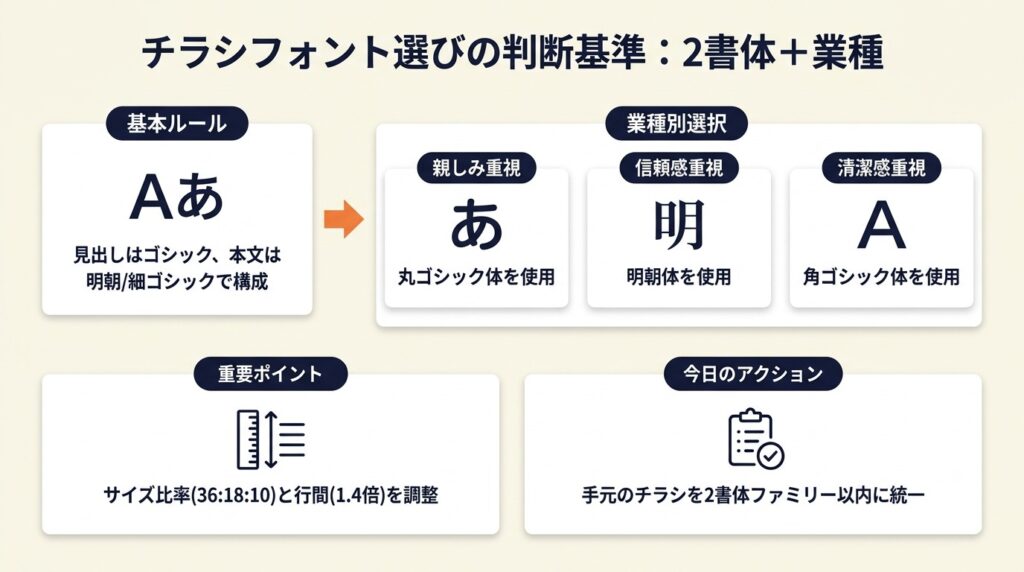
チラシに使うフォントは、ゴシック体・明朝体・丸ゴシックの3系統を業種で使い分けるだけで、読まれるチラシになります。この記事では初心者でも迷わない選び方から業種別おすすめまで7選で解説します。
この記事でわかること
3系統の使い分けルールを知ることで、フォント選びで迷う時間をゼロにできます。業種別5パターンを参照するだけで、読み手の印象と業種がぴったり合うフォントを即座に選べます。商用利用可の無料フォント7選とライセンス確認の2ステップも分かります。
この記事の結論
チラシのフォント選びで最も押さえるべきは「1チラシ2書体ルール」です。ゴシック体を見出しに、細ゴシックまたは明朝体を本文に割り当てるだけで、初心者でも読みやすいチラシが仕上がります。業種別の判断基準は「親しみ重視なら丸ゴシック、信頼感重視なら明朝体、汎用性重視なら角ゴシック」と覚えておけば、フォント選びで迷う場面は大幅に減ります。
今日やるべき1つ
手元のチラシ原稿を開き、見出しと本文のフォントが異なる書体ファミリーになっているか確認してください。同じファミリー内で太さだけ変えるだけで、まとまりが生まれます(5分)。
チラシ フォントは3系統で使い分ける
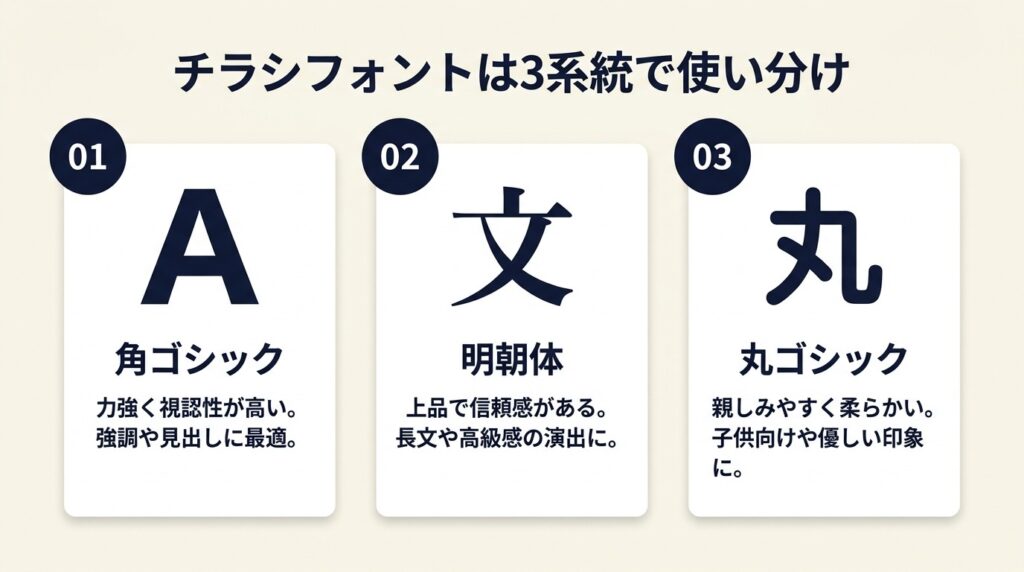
和文フォントだけでも数千種類が存在するため、選択肢の多さに圧倒されるのは自然です。ただし、覚えるべき系統は3つだけです。角ゴシック・明朝体・丸ゴシックの用途と特徴を把握すれば、どんな業種のチラシでも判断に迷わずフォントを選べます。
角ゴシックは見出しに最適なフォント
角ゴシック体は縦横の線幅がほぼ均等で、遠くから見ても文字の輪郭が崩れにくい構造を持っています。メイリオ・游ゴシック・ヒラギノ角ゴシックが代表格で、いずれもOSに標準搭載されているため追加費用なしで使えます。見出しに角ゴシックのBoldウェイトを使うと、A4チラシを腕の長さ分(約60cm)離して見ても文字が判読できる水準の視認性が確保できます。全体をゴシックで統一すると文字の密度感が均一になりすぎて重要箇所が埋もれる点は意識しておいてください。
明朝体は女性向け・高級感チラシで読みやすいフォント
明朝体は横線が細く縦線が太いという線の強弱と、文字末端の「うろこ」と呼ばれる三角形の飾りが特徴です。游明朝・ヒラギノ明朝が代表例で、エステ・ジュエリー・飲食の高単価メニューを訴求するチラシで特に効果を発揮します。本文への使用は12pt以上を確保してからにしてください。小サイズでは横線が潰れて読みにくくなります。
丸ゴシックは子ども向け・親しみやすさを出すフォント
丸ゴシックはゴシック体の線幅均等さを保ちつつ、文字の角を丸く処理したフォントです。Rounded M+ややさしさゴシックが代表格で、幼稚園・保育園の案内、地域イベント、子育て支援サービスのチラシで採用されることが多い書体です。ビジネス向けや高額商品のチラシに使うと「軽い印象」に見える場合があるため、業種との相性を事前に確認してください。
手書き風・筆書体は強調ポイント限定で使うフォント
ふい字・てがき風フォント・毛筆系フォントは、チラシ全体ではなく「本日限り」「数量限定」などの強調コピーに1箇所だけ使うのが基本です。2箇所以上に使うと読み手の視線が散漫になり、どこが最も重要なメッセージかが伝わらなくなります。「1チラシで1カ所限定」と覚えておくだけで、乱雑な印象を防げます。なお、数字フォントのおしゃれな変え方についても参考にすると、価格表記部分の印象が格段に向上します。
▶ 今すぐやること: 手持ちのチラシを開き、使用フォントが「ゴシック系」「明朝系」「その他」の何系統かを数えてください。3系統以上あれば今日中に2系統以内に絞る(10分)
よくある質問
Q: ゴシック体と明朝体はどちらが読みやすいですか?
A: 用途で判断してください。遠くから見るポスター・見出しにはゴシック体、長い本文テキストには明朝体が適しています。初心者はまずゴシック体1系統に絞るのが最もシンプルな出発点です。
Q: チラシに使うフォントは何種類まで使っていいですか?
A: 原則として1チラシあたり2書体ファミリーまでです。同じファミリーの中でRegular・Bold・Lightを使い分けるのは問題ありません。3書体以上になると統一感が崩れる原因になります。
業種別チラシ フォントは5パターンで選ぶ
業種ごとに読み手が無意識に期待している「印象の文法」があります。それに外れたフォントを使うと、内容より先に「なんか違和感がある」と感じさせてしまいます。以下の5パターンを参照して、業種に合ったフォントを即座に選んでください。
飲食店チラシは明朝体か手書き風で食欲を刺激するフォント
飲食店のチラシで最もよく使われる組み合わせは、キャッチコピーに手書き風フォント(ふい字・やさしさゴシック)、店名・メニュー名にヒラギノ明朝、価格や営業時間に游ゴシックという構成です。手書き風は「手作り感・温かみ」を演出し、明朝体は「素材へのこだわり・上品さ」を伝えます。客単価3,000円以上のフレンチやイタリアンでは手書き風を避け、明朝体を中心にすると価格帯に合った品格が出ます。
不動産・建築チラシは明朝体かDINで信頼感を出すフォント
不動産・建築業界のチラシで選ばれることが多いのは、游明朝・ヒラギノ明朝と欧文サンセリフ(DIN・Helvetica)の組み合わせです。明朝体は「誠実さ・長期的な信頼」を想起させる書体で、高額取引を伴う不動産の購買心理に合っています。物件名や価格の数値部分にDINなどの欧文フォントを使うと、和欧混在の文字列がすっきりまとまります。不動産・金融系では丸ゴシックの使用は避けてください。「カジュアルすぎて信用感が下がる」と感じる読み手が一定数います。
子ども・教育向けチラシは丸ゴシックで親しみを出すフォント
幼稚園・学習塾・子育てイベントのチラシでは、Rounded M+・やさしさゴシック・キッズフォントが定番です。丸ゴシックは視覚的なやさしさだけでなく、保護者が「安心・安全な場所」と感じるデザイン上の信号として機能します。本文テキストは最低10pt以上を確保してください。8pt以下になると丸い字形が潰れて逆に読みにくくなります。
医療・健康チラシはゴシック体のみで清潔感を出すフォント
病院・クリニック・薬局・健康食品のチラシでは、手書き風や筆書体の使用を避け、游ゴシック・ヒラギノ角ゴシックのみで統一するのが基本です。医療分野で読み手が求めているのは「正確さ・清潔さ・信頼性」であり、フォントの装飾性は逆効果になります。文字色も黒・紺・グレーに絞り、フォントの種類を増やす代わりにウェイト(太さ)の差で見出しと本文を区別する方法が最もシンプルに機能します。
美容・エステチラシはセリフ系明朝と細ゴシックで女性向け高級感を出すフォント
美容院・エステ・ネイルサロンのチラシでは、ロゴたいぷゴシック・丸明オールド・ヒラギノ明朝といった繊細な線のフォントが好まれます。BoldウェイトよりLightやRegularウェイトを全面に使うことで、余白と細い文字が共鳴して高級感が生まれます。同じデザインレイアウトでもフォントをBoldから明朝Regularに変えるだけで、仕上がりの印象が格段に上がります。チラシのデザイン作成にはCanvaのテンプレートを活用すると、フォントペアリングを効率よく確認できます。
▶ 今すぐやること: 自分の業種を上記5パターンから選び、推奨フォントのうち1つをCanvaまたはWordでテスト入力して印刷プレビューを確認する(10分)
よくある質問
Q: 飲食店のチラシで明朝体と手書き風はどちらが効果的ですか?
A: 業態の価格帯で判断するのが最適です。ランチ1,000円以下のカジュアルな飲食店には手書き風、客単価3,000円以上の和食・フレンチ・イタリアンには明朝体を選ぶと、価格帯と印象が一致します。
Q: 医療チラシで明朝体を使ってはいけないですか?
A: 絶対禁止ではありません。ただし、明朝体の「繊細な横線」が小サイズで潰れやすいため、高齢者向け医療チラシでは読みにくくなるリスクがあります。確実に読んでもらいたい場合はゴシック体を優先してください。
チラシ フォント選びの失敗を3分で診断
「自分のチラシが今どの失敗パターンに当てはまるか」を判定できると、修正ポイントがすぐに特定できます。以下の質問に順番に答えることで、3分以内に対処すべき問題が明確になります。
Q1: チラシに使っているフォントの書体ファミリーは何種類ですか?
3種類以上 → Q2へ。2種類以下 → Q3へ。
Q2: 3種類以上使っているフォントは、それぞれ「見出し用」「本文用」「強調用」と役割が明確に決まっていますか?
役割が決まっていない →Result A(書体の役割が未定義)。役割が決まっている → Q3へ。
Q3: 最も小さい文字サイズは何ptですか?
8pt以下 →Result B(サイズ不足で潰れリスクあり)。9pt以上 → Q4へ。
Q4: 業種と使用フォントの印象は一致していますか?(例:医療×手書き風、不動産×丸ゴシック)
一致していない →Result C(業種ミスマッチ)。一致している →Result D(現状は適切)。**
Result A: 今すぐフォントを2書体ファミリーに絞ってください。見出しには角ゴシックBold、本文には同じファミリーのRegularかLightを使うだけで統一感が生まれます。所要時間15分で修正できます。
| 印刷後の品質が心配 | 50%縮小印刷で試し刷りして潰れを確認する | 10分 |
チラシ フォントに関するよくある質問
Q: チラシのフォントサイズは最低何ptにすればいいですか?
A: 本文テキストの最低ラインは10ptです。高齢者をメインターゲットとするチラシでは12〜14ptを基準にしてください。キャプション・注意書きは8ptまで許容されますが、8pt未満は印刷で潰れるリスクが高まります。
Q: チラシに使うフォントはいくつまで使っていいですか?
A: 2書体ファミリーまでが原則です。例外として、強調コピー1箇所のみ手書き風フォントを使う場合は合計3書体ファミリーまで許容されます。それ以上は視覚的な統一感が崩れる原因になります。
Q: チラシの見出しにはどのフォントが最も選ばれていますか?
A: 業種を問わず多く選ばれているのは角ゴシック体(ヒラギノ角ゴシック・游ゴシック・メイリオ)のBoldウェイトです。OSに標準搭載されており追加費用不要なうえ、遠距離視認性が高いことが選ばれ続けている理由とされています。また、日本語フォントの無料おすすめ12選では商用OKのフォントをさらに詳しく解説しているので、あわせて参考にしてください。